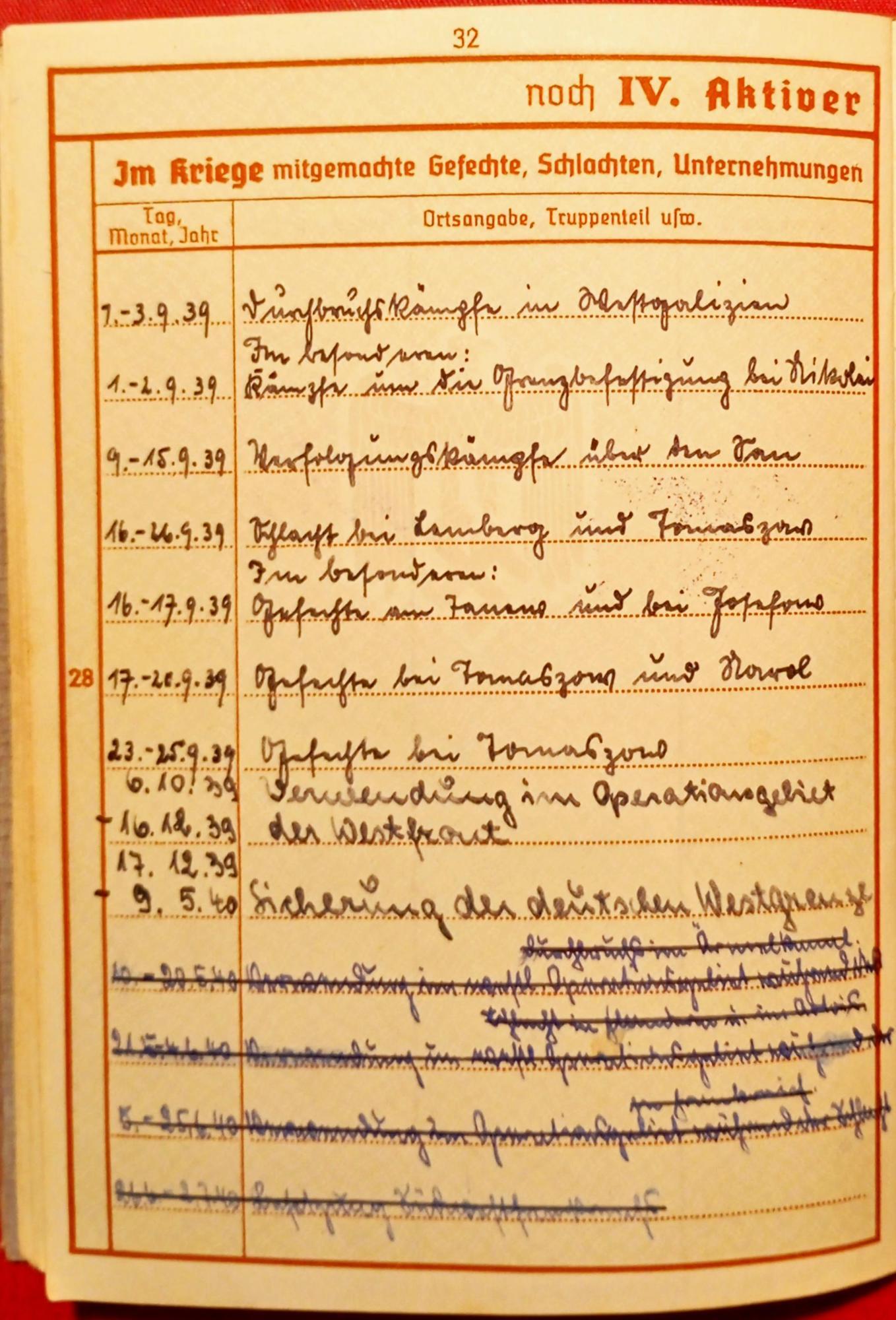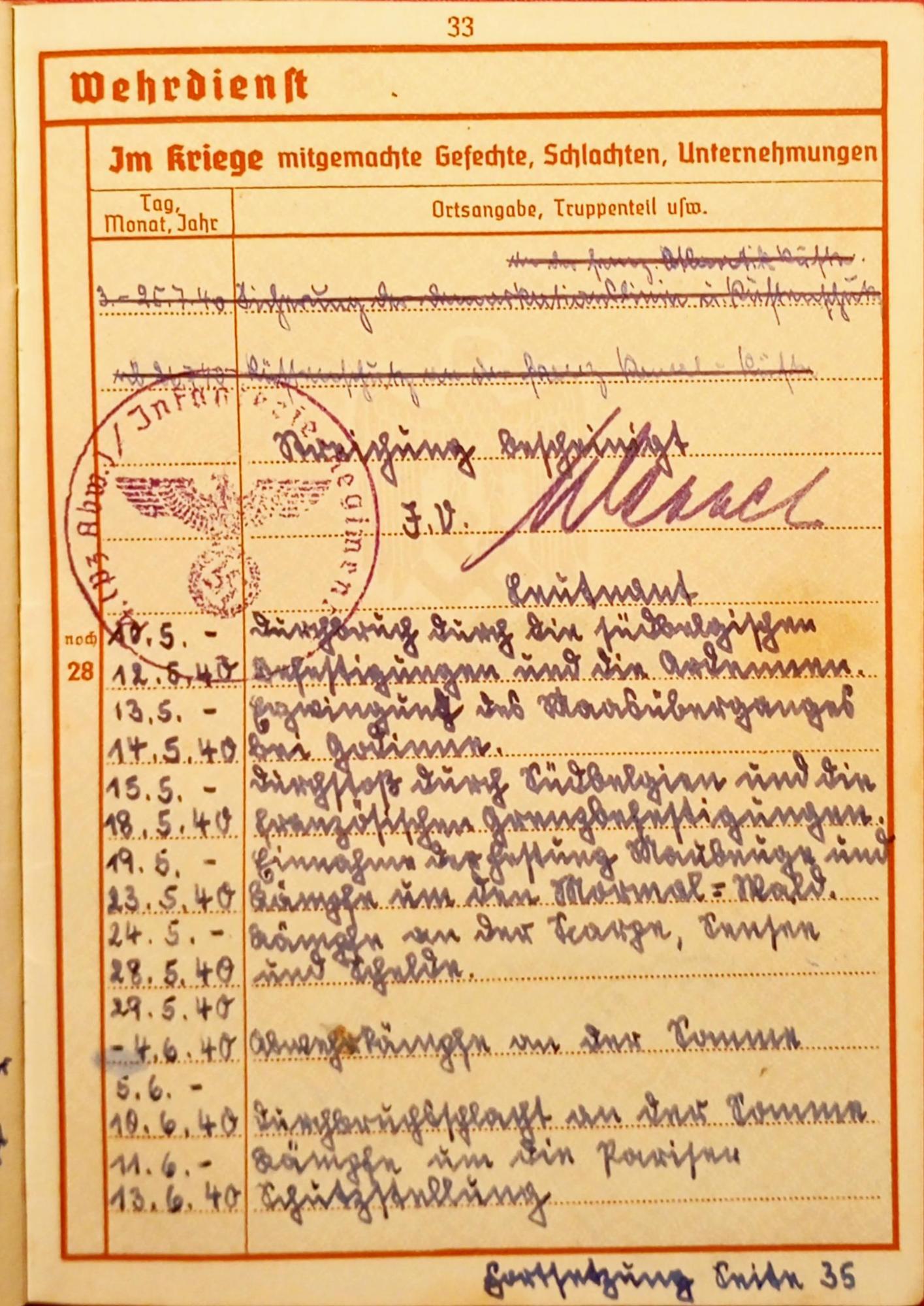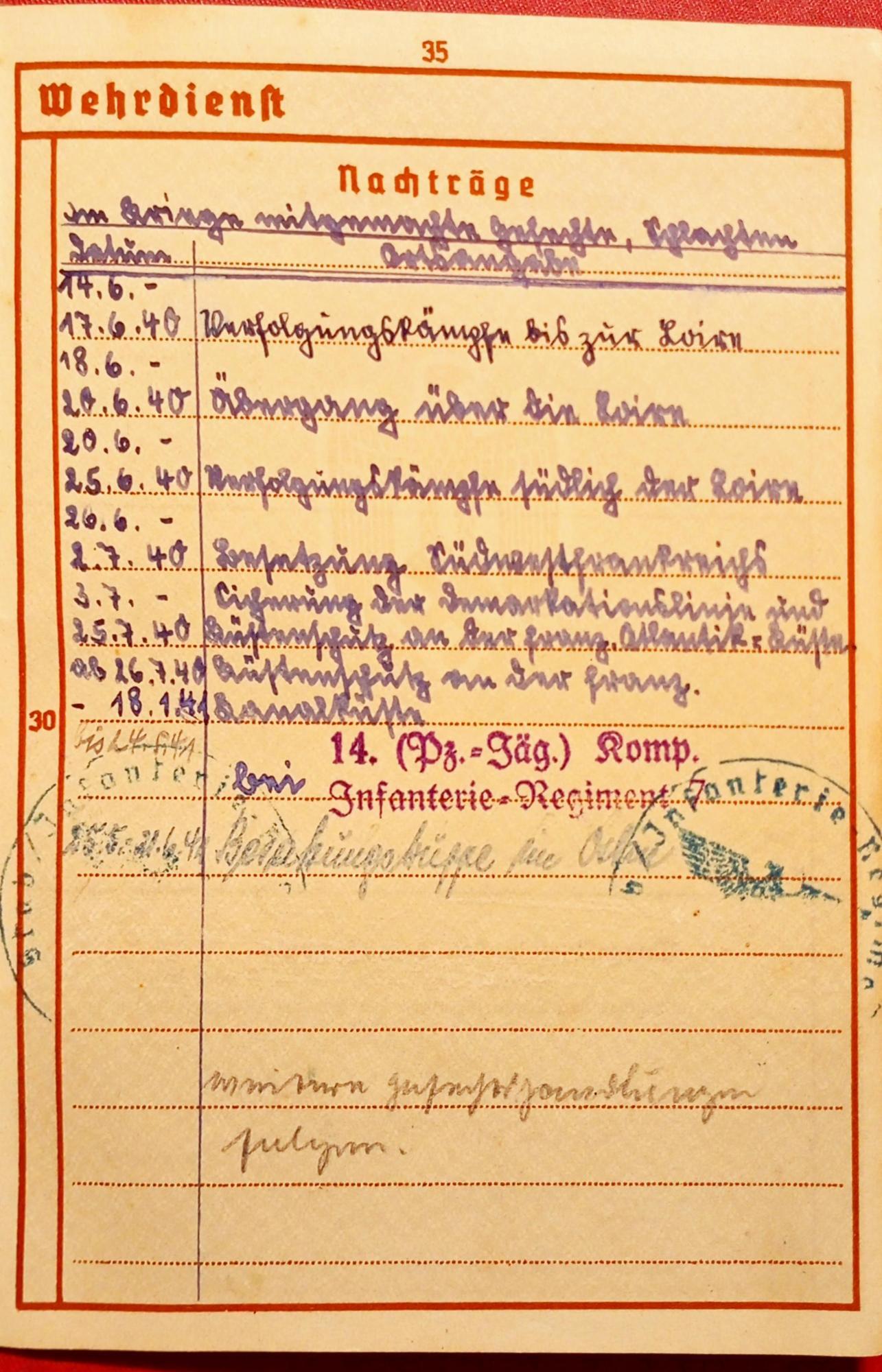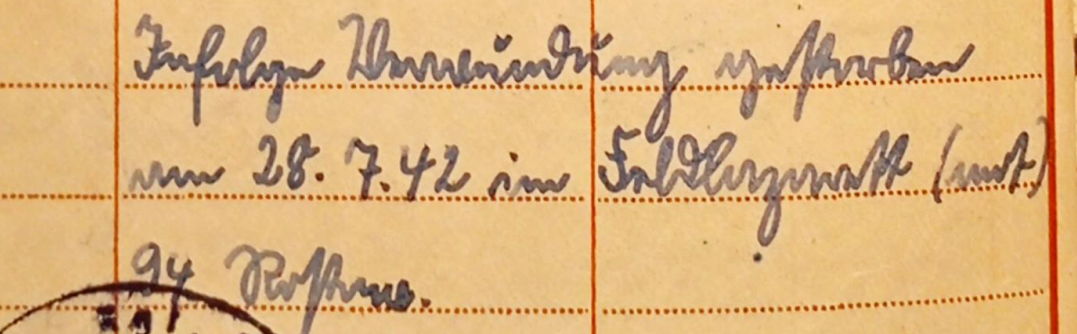
Entzifferung Wehrpass (Sütterlin)
ich habe heute den alten Wehrpass des Bruders meines Grossvaters in die Hände bekommen und ihn eingescannt.
Kann mir jemand mit der Entzifferung helfen?
Als Erstes würde mich nur dieser kurze Abschnitt auf dem Foto interessieren. Müsste sich um das Versterben im Krieg handeln.
Infolge Verwundung gestorben am 28. 7 42 im Feldlazarett…
Könntest Du mir bei der Entzifferung der Folgenden Seiten eventuell auch helfen?
Blatt 35, Nachträge:
14.6. – 17.6.40
Verfolgungskämpfe bis zur Loire
18.6. – 20.6.40
Übergang über die Loire
20.6. – 25.6.40
Verfolgungskämpfe südlich der Loire
26.6. – 2.7.40
Entsetzung (?) Südwestfrankreichs
3.7. – 25.7.40
Sicherung der Demarkationslinie und Küstenschutz an der franz. Atlantik-Küste
ab 26.7.40 – 18.1.41
Küstenschutz an der franz. Kanalküste
Seite 32 (Datumsangaben lasse ich weg):
Durchbruchskämpfe in Westgalizien
Im besonderen: Kämpfe um die Grenzbefestigung bei Nikolai
Verfolgungskämpfe über den San
Schlacht bei Lemberg und Tomaszow
Im besonderen: Gefechte am Tanew und bei Josefow
Gefechte bei Tomaszow und Narol
Gefechte bei Tomaszow
Verwendung im Operationsgebiet der Westfront
Sicherung der deutschen Westgrenze
Die Schrift ist gut lesbar. Falls es noch mehr Familiendokumente dieser Art gibt, lohnt es sich, ein Kurrentalphabet danebenzulegen und selbst zu entziffern.
Seite 33:
Durchbruch durch die südbelgischen Befestigungen und die Ardennen
Erzwingung des Maasüberganges bei Godinne
Durchstoß durch Südbelgien und die französischen Grenzbefestigungen
Einnahme der Festung Maubeuge und Kämpfe um den Mormal-Wald
Kämpfe an der Scarpe, Sensee und Schelde
Abwehrkämpfe an der Somme
Durchbruchsschlacht an der Somme
Kämpfe um die Pariser Schutzstellung